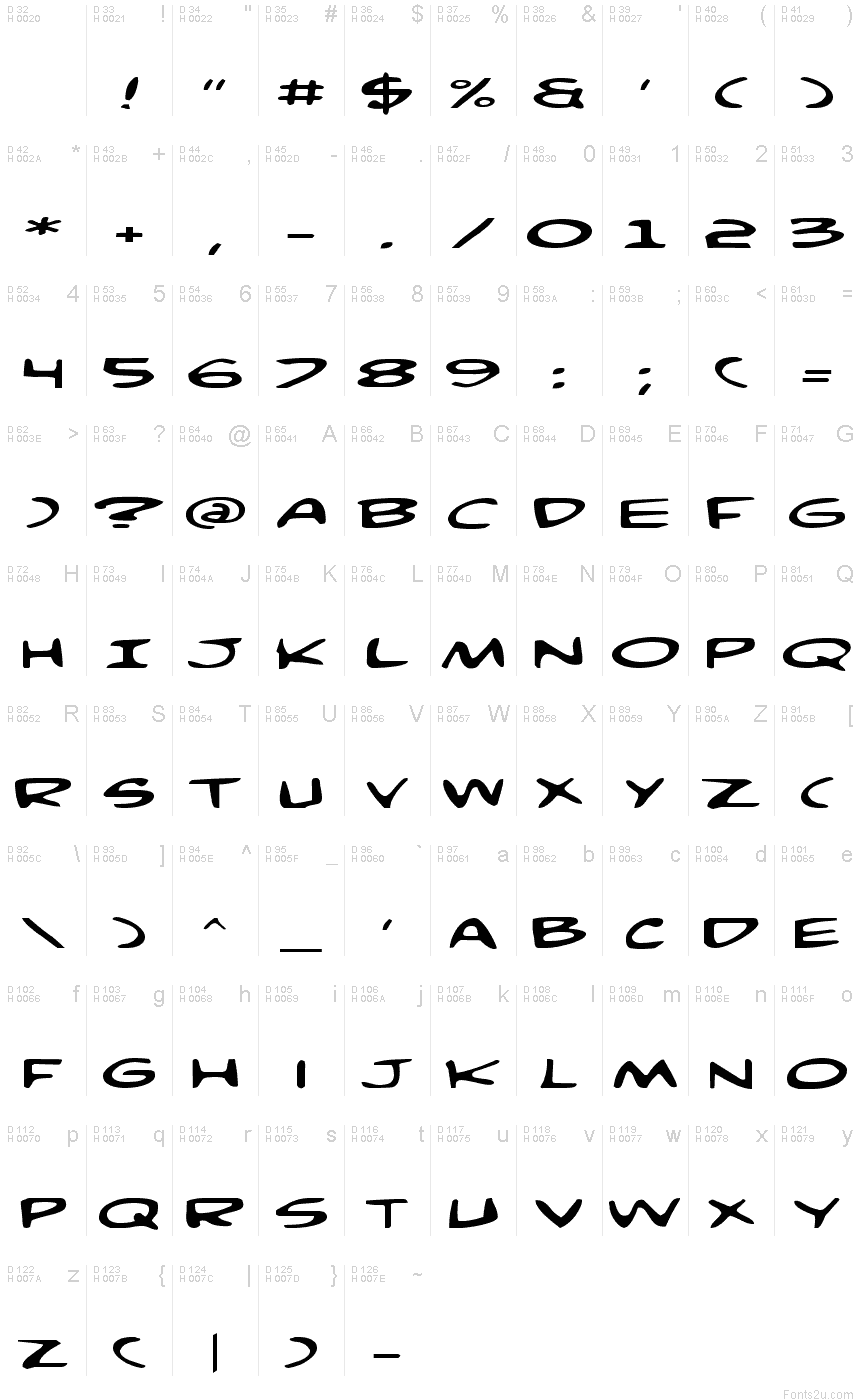
Comic Book Commando Expanded
Comic Book Commando Expanded od Iconian Fonts to darmowy font typu display w stylu komiksowym. Wchodzi z przytupem dzięki szerokim, rozciągniętym literom i dynamicznemu pochyleniu – niczym efekt dźwiękowy na komiksowym kadrze. Kreska wygląda jak rysowana tuszem, jest wyrazista, ale nie ociężała, dzięki czemu nagłówki pozostają czytelne i efektowne.
Wykorzystaj Comic Book Commando Expanded na okładkach komiksów, plakatach dla dzieci, tytułach w stylu arcade, miniaturach na YouTube, wlepkach, nagłówkach w grach czy ulotkach. Ten darmowy font świetnie sprawdza się w krótkich hasłach, gdzie jego dodatkowa szerokość robi robotę. Połącz go z prostym, bezszeryfowym krojem w tekście głównym i dodaj nagłówkowi trochę światła (tracking), aby całość mogła odetchnąć.